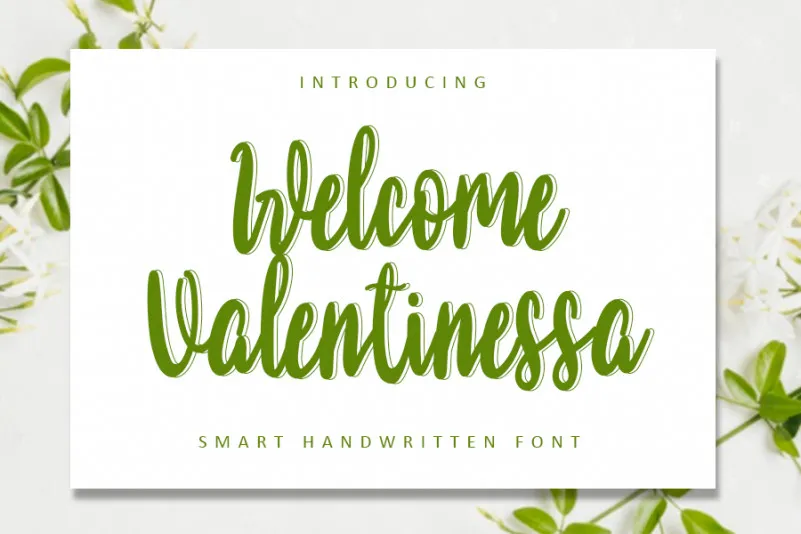
Welcome Valentinessa Script Font – Fonte Grátis
Welcome Valentinessa Script Font
A Welcome Valentinessa Script Font é uma delicada e suave fonte escrita a mão, ideal para qualquer projeto que precise de um toque romântico e personalizado. Suavemente delicada e rica em alegria, esta fonte será perfeita para escrever convites de casamento, cartas ou qualquer outra design que possa precisar de um touch personalizado. Com seu aspecto suave e encantador, essa fonte traz uma atmosfera morna e descontraída ao seu projeto. Ela é ideal tanto para se tornar a estrela do design quanto para complementá-lo. Perfect para momentos importantes como o grande dia, bem como para qualquer momento romântico de sua vida, esta fonte Welcome Valentinessa Script Font é um must-have para designers e amantes da arte que desejam dar um toque único à suas criações.